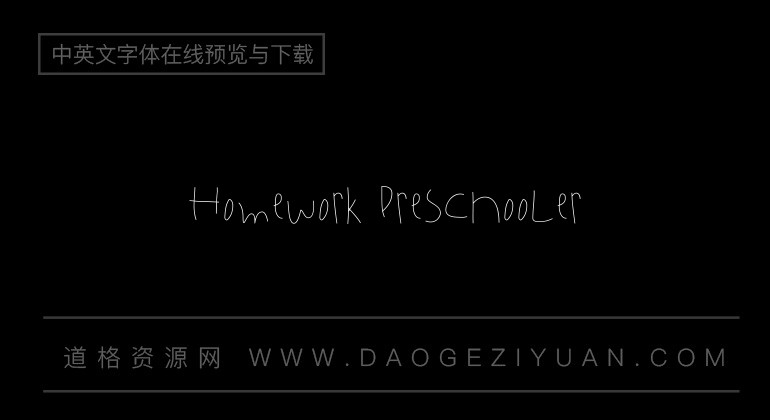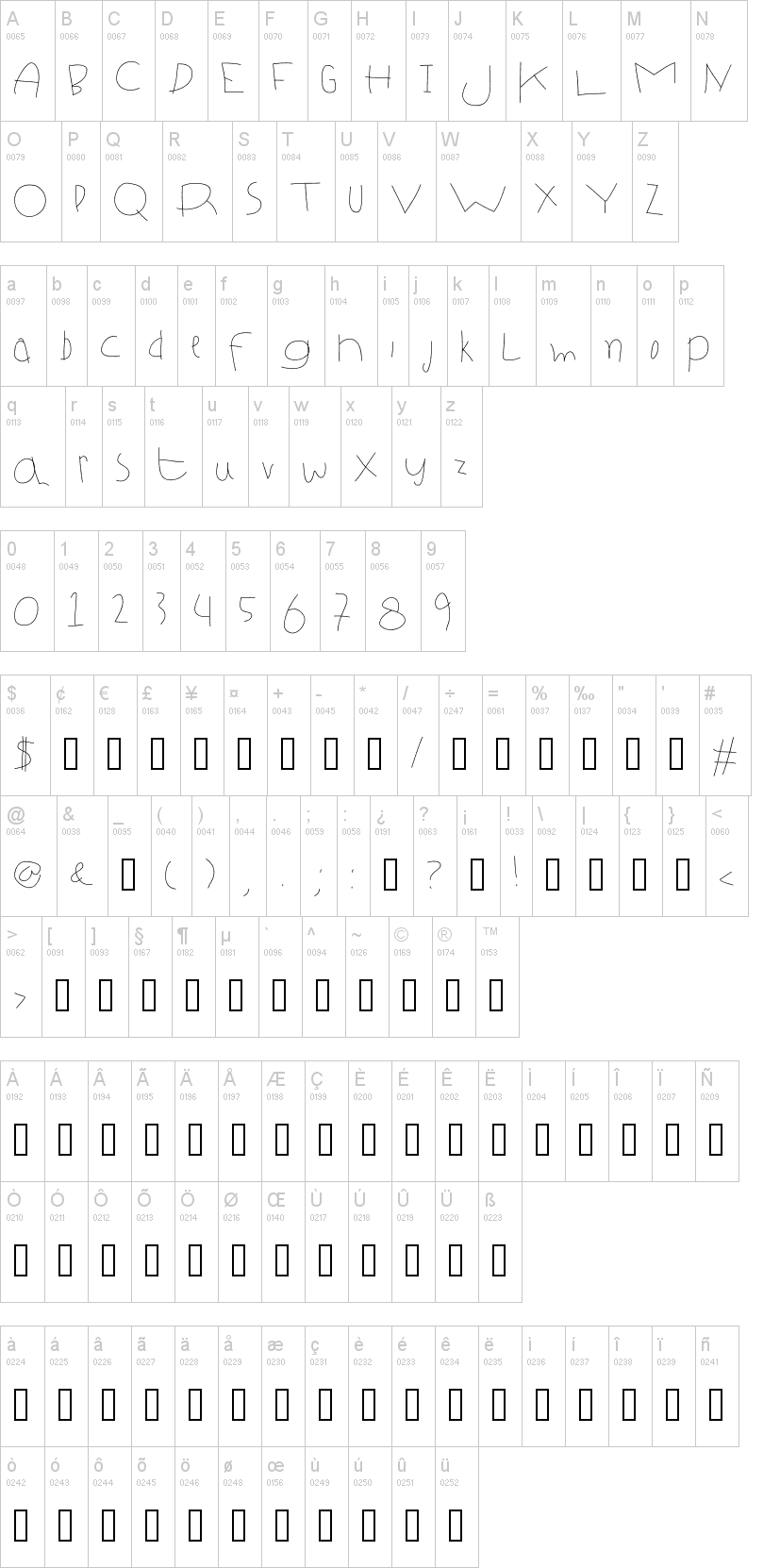
Homework Preschooler 是一种手写字体,旨在模仿小学生的书写风格。它是 Homework 字体家族中的一员,由设计师 Fabian Fohrer 在 2012 年创建。 这种字体有着非常独特的外观,仿佛是由小学生用铅笔书写而成。它具有一些特殊的特征,如不规则的笔画、变形的字形和不对称的字符间距,这些特点使它看起来更加自然和手写风格。 Homework Preschooler 字体非常适合用于儿童相关的设计、教育类应用、出版物或其他需要营造童趣、童真氛围的场合。此外,它还可以用于 DIY 手账、手写笔记等个人创意项目中。内容介绍
Homework Preschooler是一款非常不错的手写艺术字体,具有很好的视觉感,适合于文化类的宣传设计、商业类品牌的广告和产品包装设计以及个性化文字排版等较多场景。